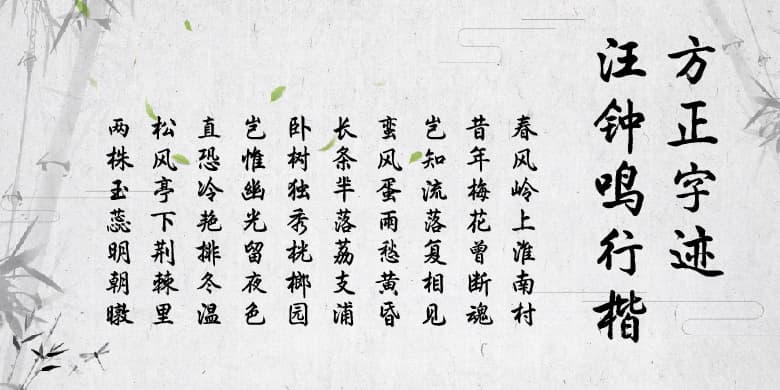
方正字迹-汪钟鸣行楷
品牌:方正字迹设计师:汪钟鸣发行时间:2021字库编码:简繁扩展(GBK)、大陆简体(GB2312-80)分类:常规书写·毛笔字体属性:精品字
《方正字迹-汪钟鸣行楷》,该字体用毛笔书写,坚持中国传统书风,字体端庄规范大气,适用于大型广告、商店招牌、宣传栏及各类装饰等。
作者汪钟鸣,出生于书香门第,专长书法,擅长楷书、行书、草书、篆书、隶书等,兼攻书法理论。系中国书法家协会会员,中国书画院会员,中国书法艺术委员会会员,中国文化艺术发展促进会会员,安徽省书法家协会会员,文化部文化市场发展中心特聘书画家。